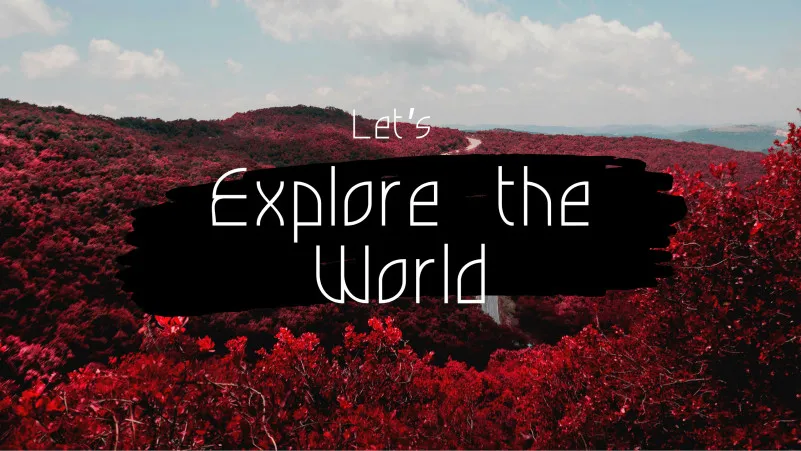
Eyesy Font – Download Grátis
A fonte ‘Eyesy Font’ é uma elegante escolha para designers que buscam uma opção moderna e imponente. Esta fonte display oferece a capacidade de personalização, permitindo que você ajuste-a conforme suas necessidades específicas, tornando-o um recurso indispensável para criar gráficos profissionais. Ideal para headlines ou qualquer conteúdo que deseje destacar visualmente, essa fonte combina modernidade com sofisticação, sendo uma ótima escolha para apresentações de PowerPoint, sites e até mesmo para uso em logotipos e materiais impressos. É perfeitamente complementada pela equipe do freefontsfamily, garantindo um design limpo e funcional que torna a experiência de criar gráficos mais gratificante.